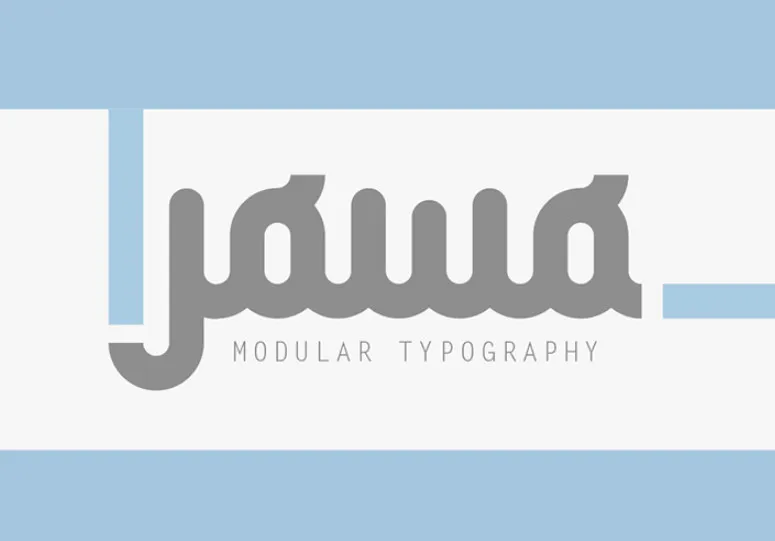
Jowo Typeface
Jowo Typeface é uma tipografia script modular criada pelo designer Hamilton. Esta tipografia traz uma sensação encantadora com detalhes atraentes. Marta Forns introduziu essa fonte para uso em cartões, impressões, logotipos, convites, ilustrações e decoração. Ela inclui letras maiúsculas e minúsculas, números, caracteres especiais e acentos. É perfeitamente adequada para projetos gráficos que valorizam um estilo elegante e sofisticado. Jowo é uma ótima opção para aqueles buscando criar trabalhos com um ar delicado e suave.